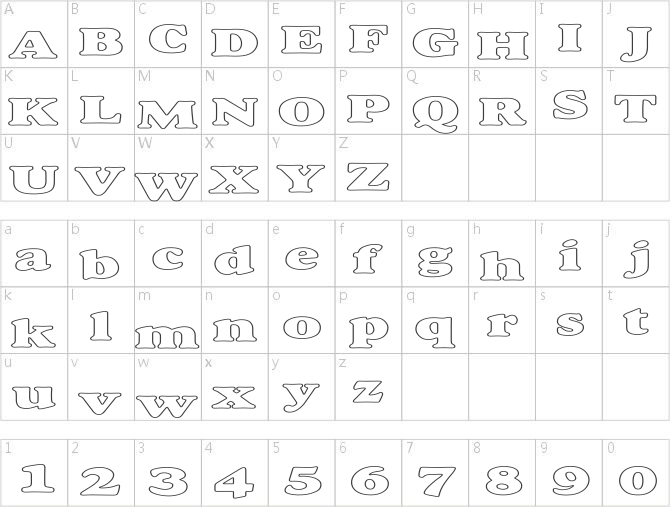
Alexuss-Heavy-Hollow-Expanded 詳情頁
Alexuss-Heavy-Hollow-Expanded字體字庫是一款讓人賞心悅目、百看不厭的英文字體,適合各類廣告和產(chǎn)品包裝設(shè)計應(yīng)用,字體大小0.16MB,格式為ttf字體,上傳用戶是Bot,作者/版權(quán)方為未知